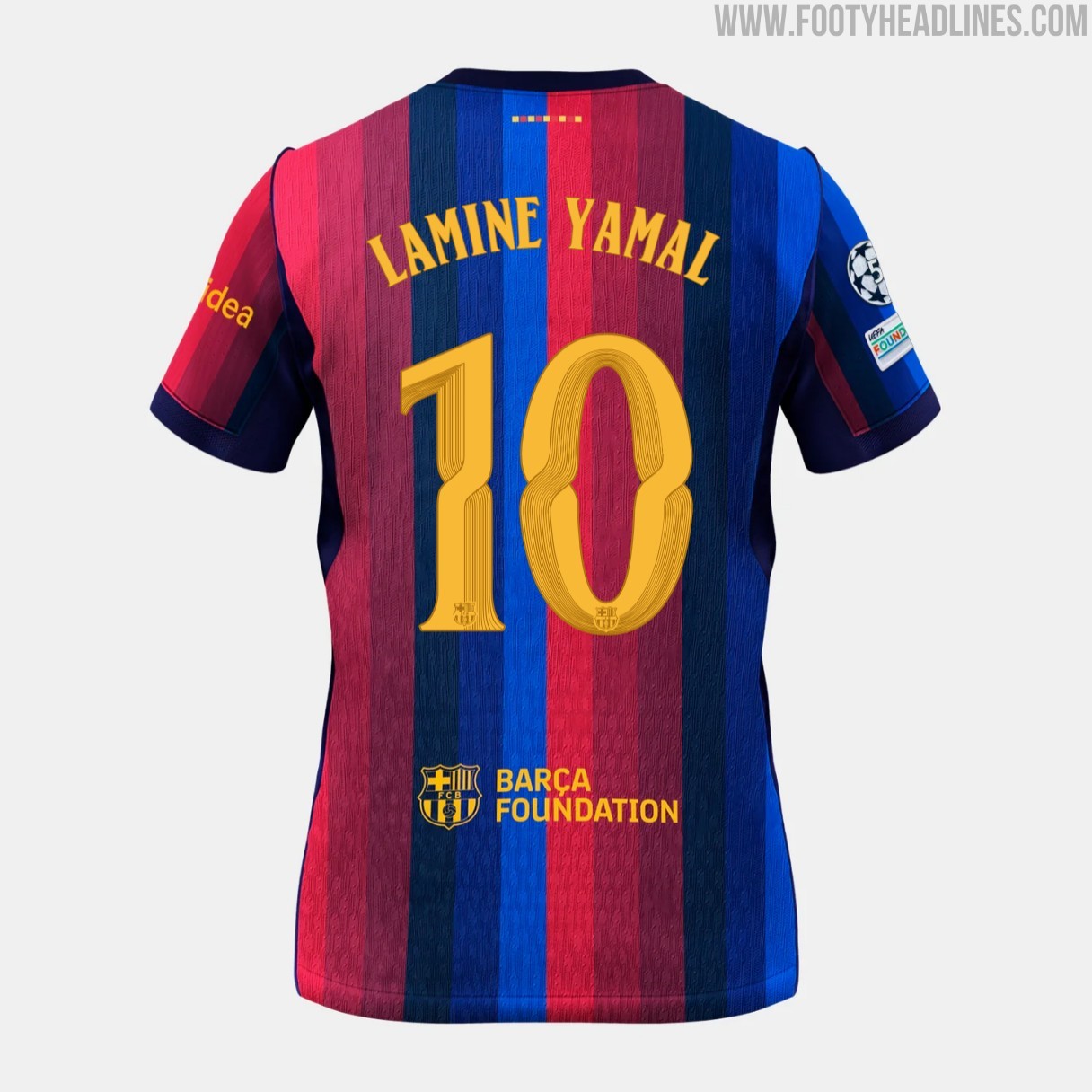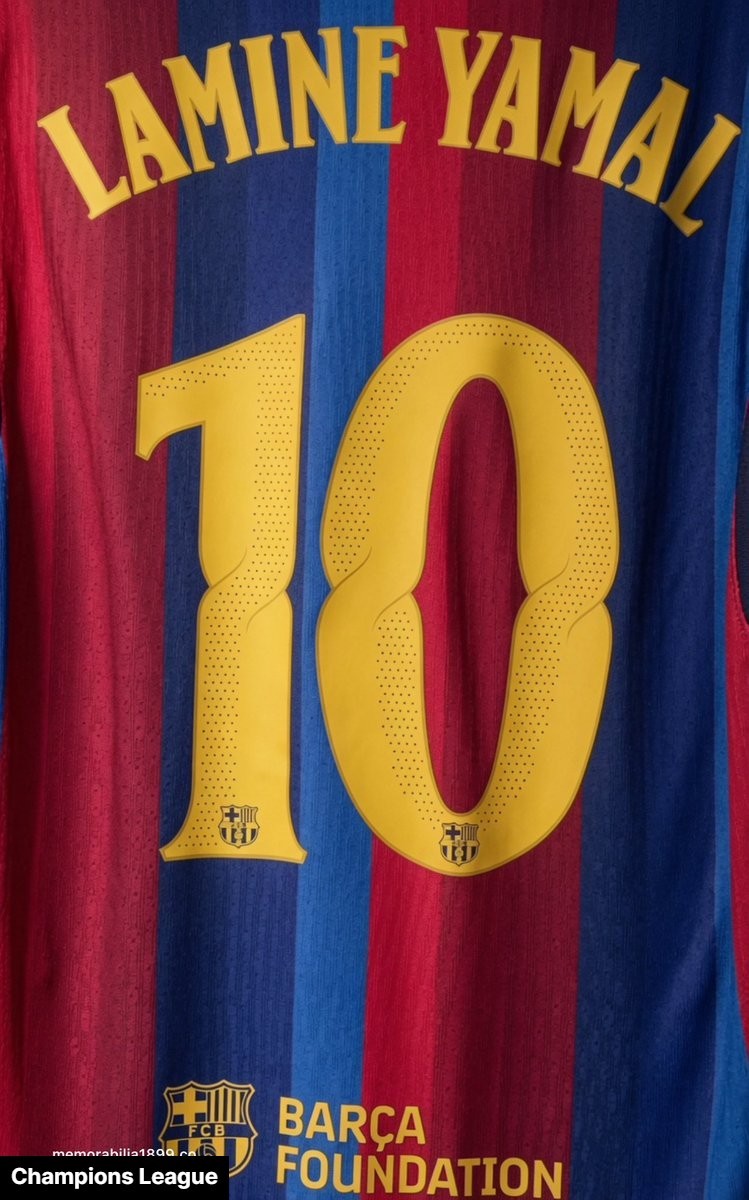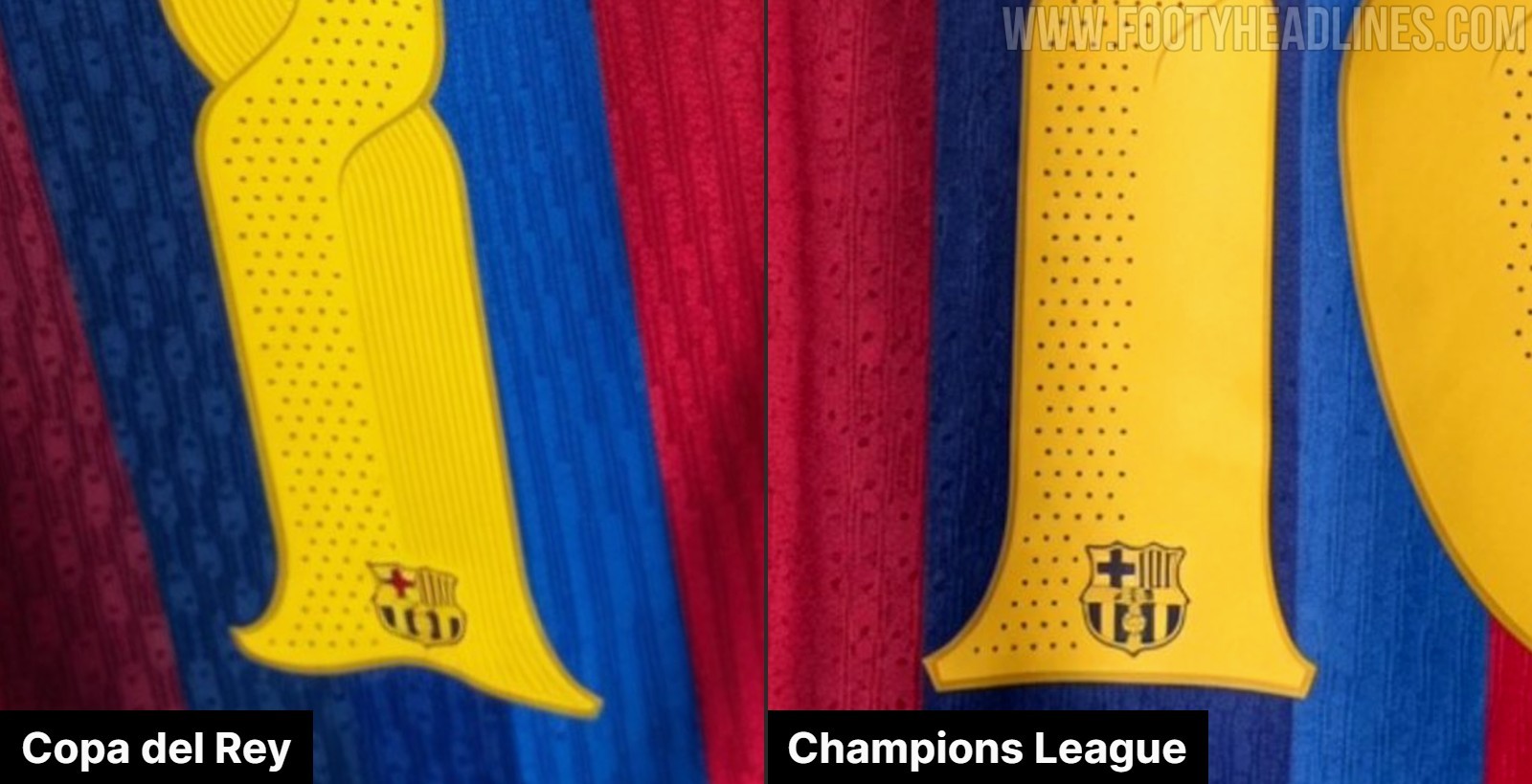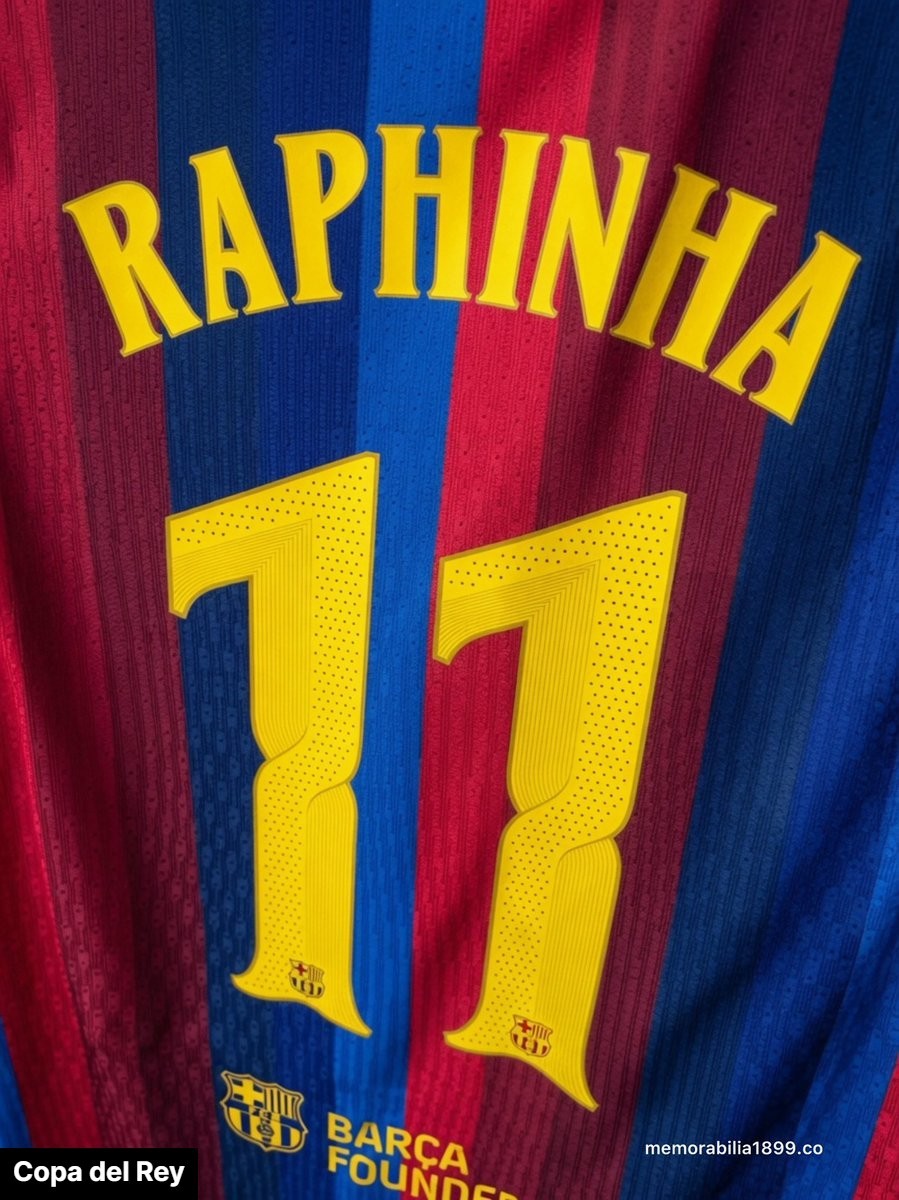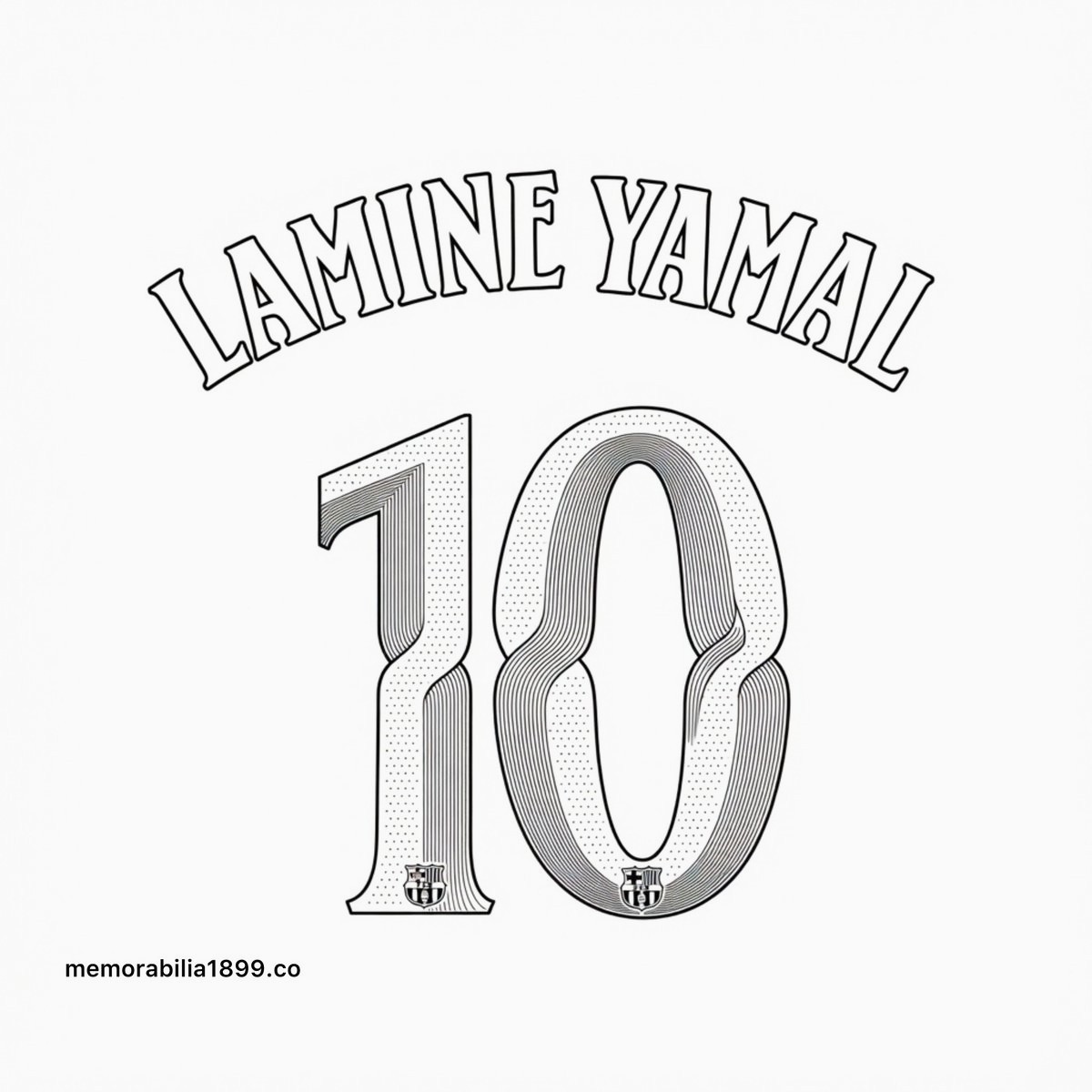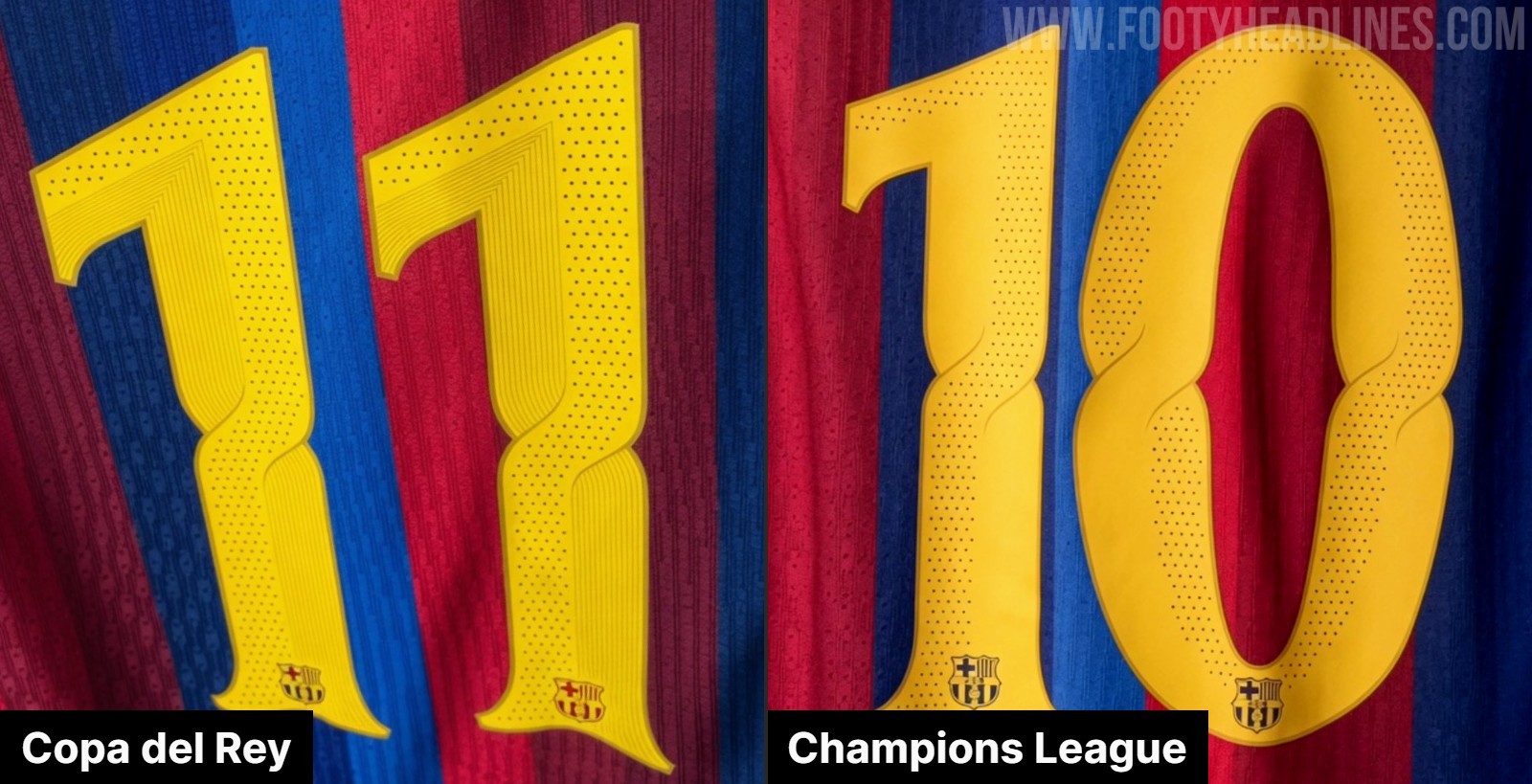
¿La tipografía de la camiseta del FC Barcelona para la Liga de Campeones 26-27 sufrirá una pequeña modificación debido a las normas de la UEFA sobre equipaciones?
• Nueva Tipografía Personalizada: El FC Barcelona introducirá una tipografía personalizada totalmente nueva para sus partidos fuera de liga en la temporada 2026-27, inspirada en el Modernismo catalán con bordes fluidos y curvas.
• Modificación por Normas UEFA: La tipografía para la Liga de Campeones del FC Barcelona 26-27 tendrá números lisos sin líneas interiores, ya que las estrictas normas de la UEFA sobre equipación no permiten las rayas decorativas presentes en la versión de Copa.
• Restricción en La Liga: El FC Barcelona no podrá utilizar esta tipografía personalizada en La Liga, donde seguirá empleando el diseño estandarizado de la competición española, reservando así el nuevo diseño artístico exclusivamente para partidos de copa y europeos.
El FC Barcelona lucirá una tipografía personalizada totalmente nueva en sus partidos fuera de liga de la temporada 2026-27. Gracias al experto en el FC Barcelona @memorabilia1899, vemos que podría haber una pequeña diferencia entre las versiones de la Copa del Rey y la Liga de Campeones de la UEFA.
¿La tipografía de la camiseta del FC Barcelona para la Liga de Campeones 26-27 sufrirá una pequeña modificación debido a las normas de la UEFA sobre equipaciones?
FC Barcelona 26-27: tipografía de la camiseta de copa frente a la de la Liga de Campeones
La nueva tipografía de la camiseta de copa del FC Barcelona para la temporada 2026-27 presenta bordes fluidos y curvas, inspirándose en gran medida en el Modernismo catalán, un reconocido movimiento artístico y literario catalán. Esta influencia le da a los nombres y números un aspecto claramente artístico y elegante, lo que la distingue de las tipografías deportivas más tradicionales y angulosas.
Aunque el diseño básico de la tipografía es el mismo, hay una diferencia notable entre las versiones que se usarán en las competiciones de copa nacionales y en la Liga de Campeones de la UEFA. La tipografía estándar para las copas, pensada para la Copa del Rey y la Supercopa de España, tiene unas sutiles rayas en el interior de los números.
Sin embargo, las estrictas normas de la UEFA sobre equipación no permiten estas rayas decorativas en el interior de los números. Por eso, la versión para la Liga de Campeones de la tipografía del Barcelona 26-27 tendrá números lisos sin líneas interiores, lo que garantiza el cumplimiento de las normas de las competiciones europeas sin dejar de mantener la silueta fluida inspirada en el modernismo.
Tipografías del FC Barcelona 26-27 para La Liga y la Copa (aquí las líneas están un poco mal)
Como es habitual, el FC Barcelona no podrá usar este tipo de letra personalizado en La Liga. El club seguirá usando la tipografía estandarizada de la liga para todos los partidos de la máxima categoría española, lo que significa que este nuevo diseño artístico se reservará exclusivamente para los partidos de copa y europeos.
Sin embargo, @memorabilia1899 dice que en la imagen no se aprecian bien las líneas sutiles, así que podría tratarse simplemente de «un error». Tendremos que estar atentos a la información definitiva.